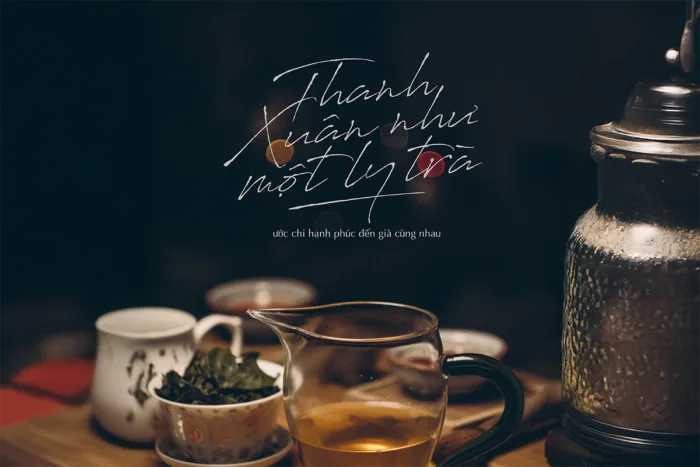
MTD Antro Vectra Việt hóa – Viết nên thanh xuân bằng những nét mềm mại
MTD Antro Vectra Việt hóa mang trong mình vẻ đẹp của chữ viết tay thanh thoát, như một dòng cảm xúc tuôn trào trên trang giấy. Những đường cong nhẹ, các nét nối uyển chuyển giúp font trở thành lựa chọn hoàn hảo cho các thiết kế giàu tính cá nhân – đặc biệt là ảnh kỷ yếu, thiệp mời hay bìa sách thơ.
Font này không chỉ đơn thuần là một kiểu chữ, mà còn là một cách để kể chuyện – kể về những năm tháng thanh xuân, những khoảnh khắc lặng thầm nhưng sâu đậm. Việc Việt hóa trọn bộ giúp bạn dễ dàng thể hiện các câu chữ tiếng Việt một cách tự nhiên và đồng bộ, không lo lỗi dấu hay mất nét.